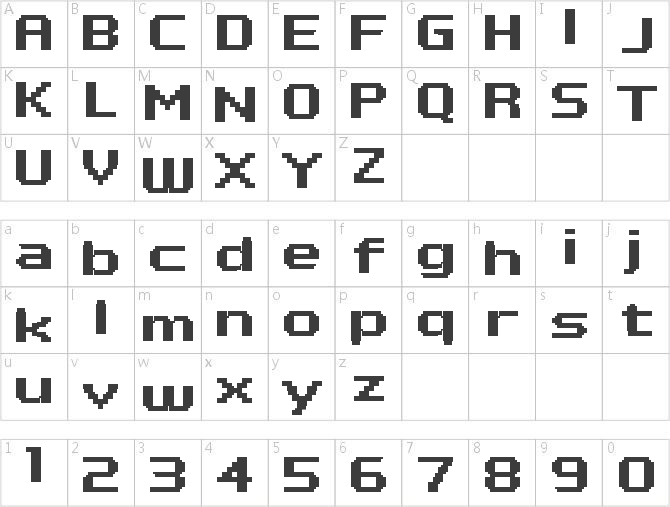
字体名称: pf_temp
pf_tempesta_seven_extended_bold
pf_tempesta_seven_extended_bold字体字库是一款让人赏心悦目、百看不厌的英文字体,适合各类广告和产品包装设计应用,字体大小0.07MB,格式为ttf字体,上传用户是志诚设计,作者/版权方为未知